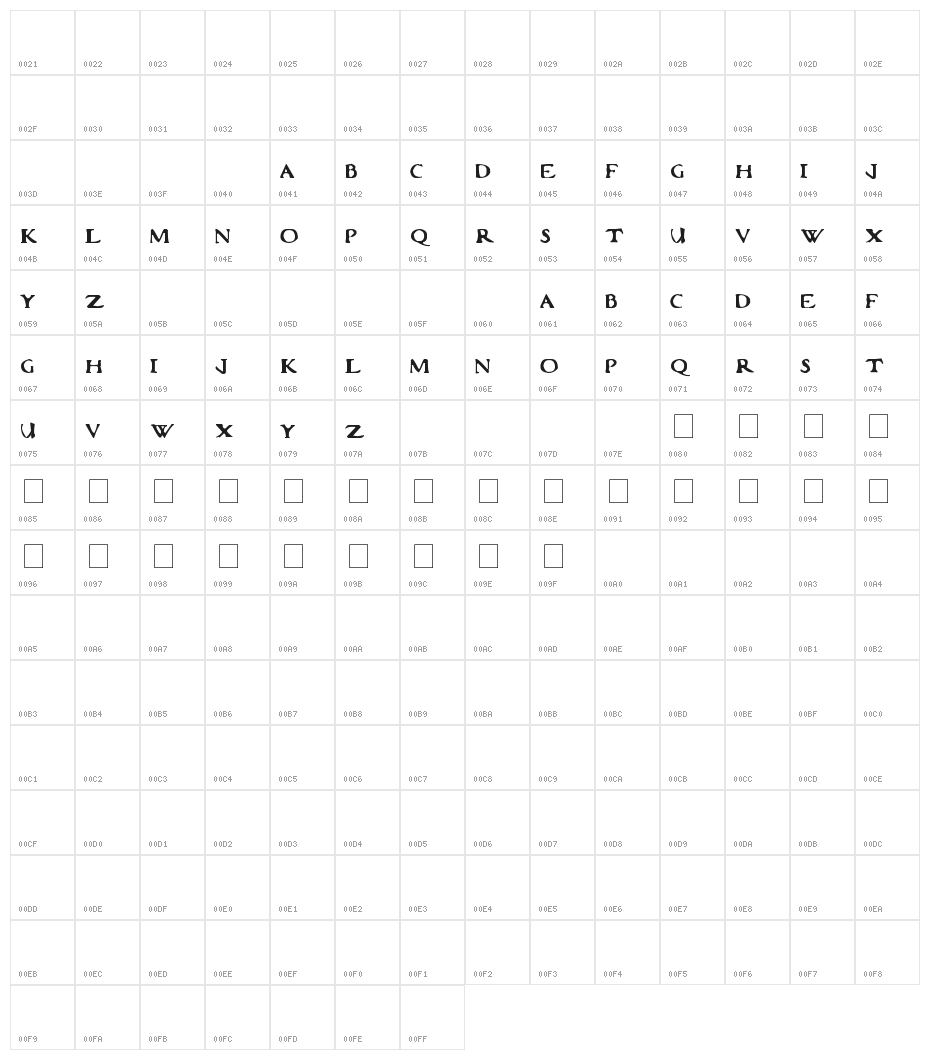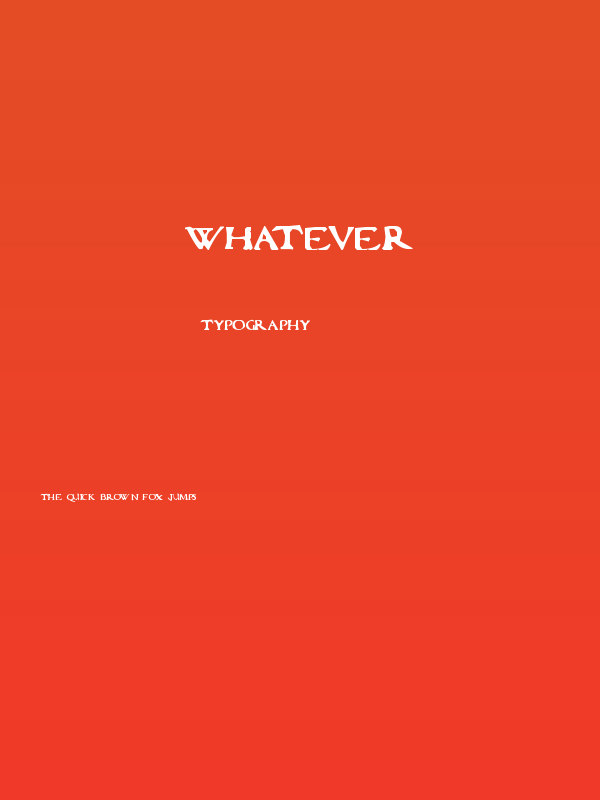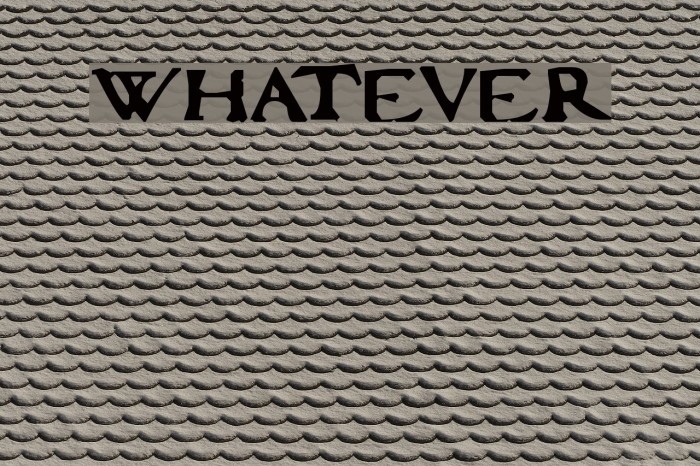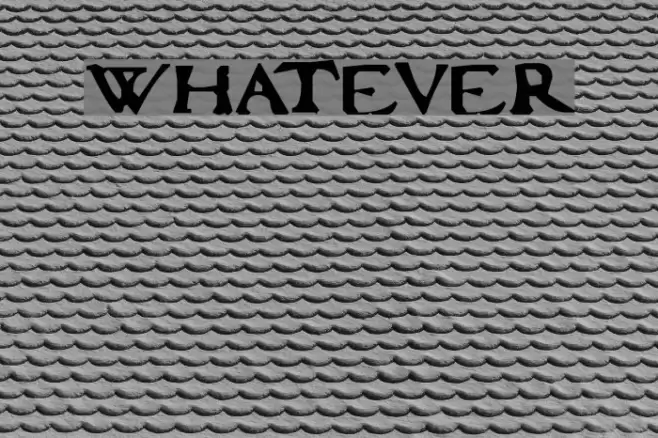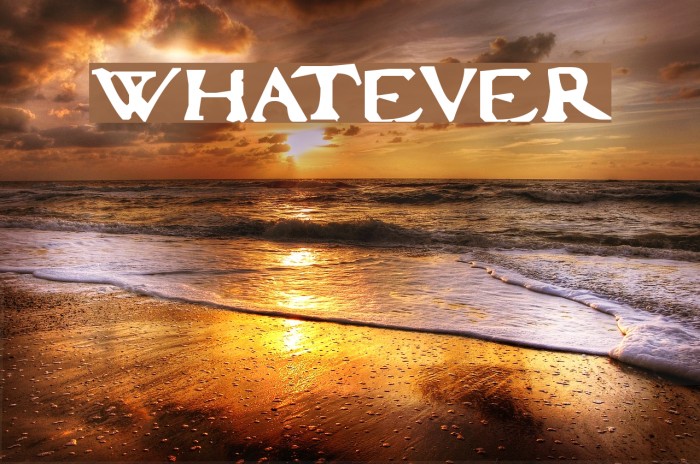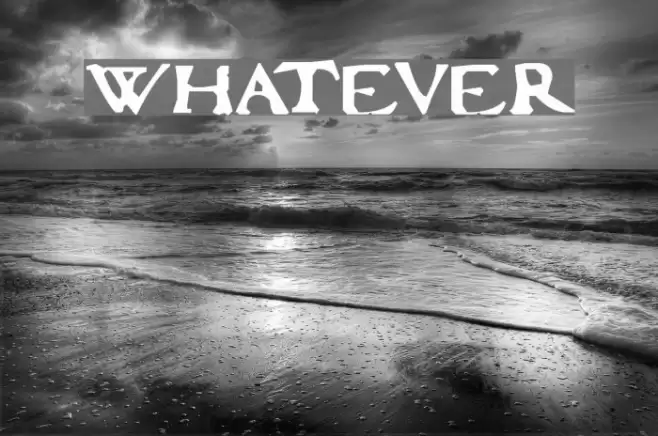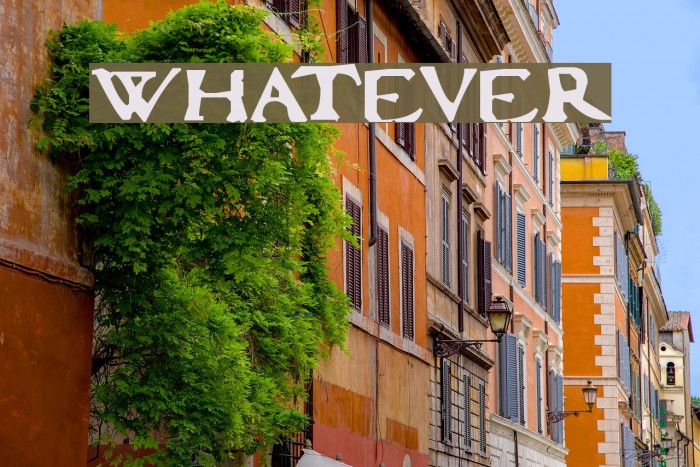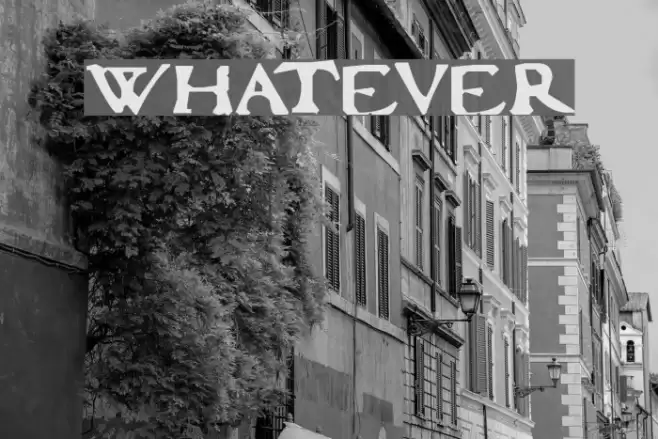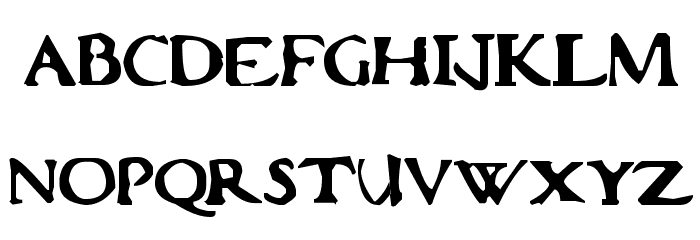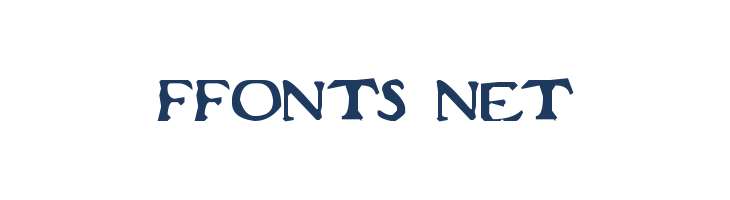
whatever Font
| النمط العام | Vintage |
| مشاريع مقترحة | Ideal for historical-themed designs, fantasy book covers, medieval event posters, or any project requiring an ancient script style. |